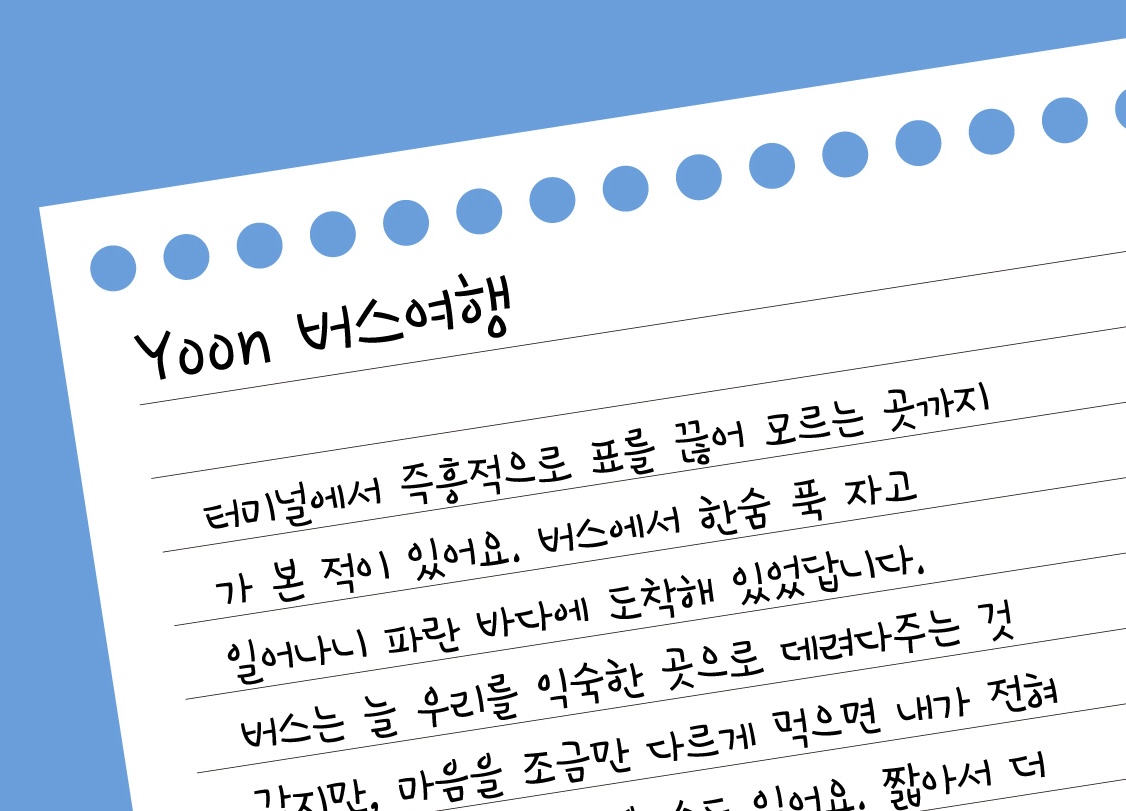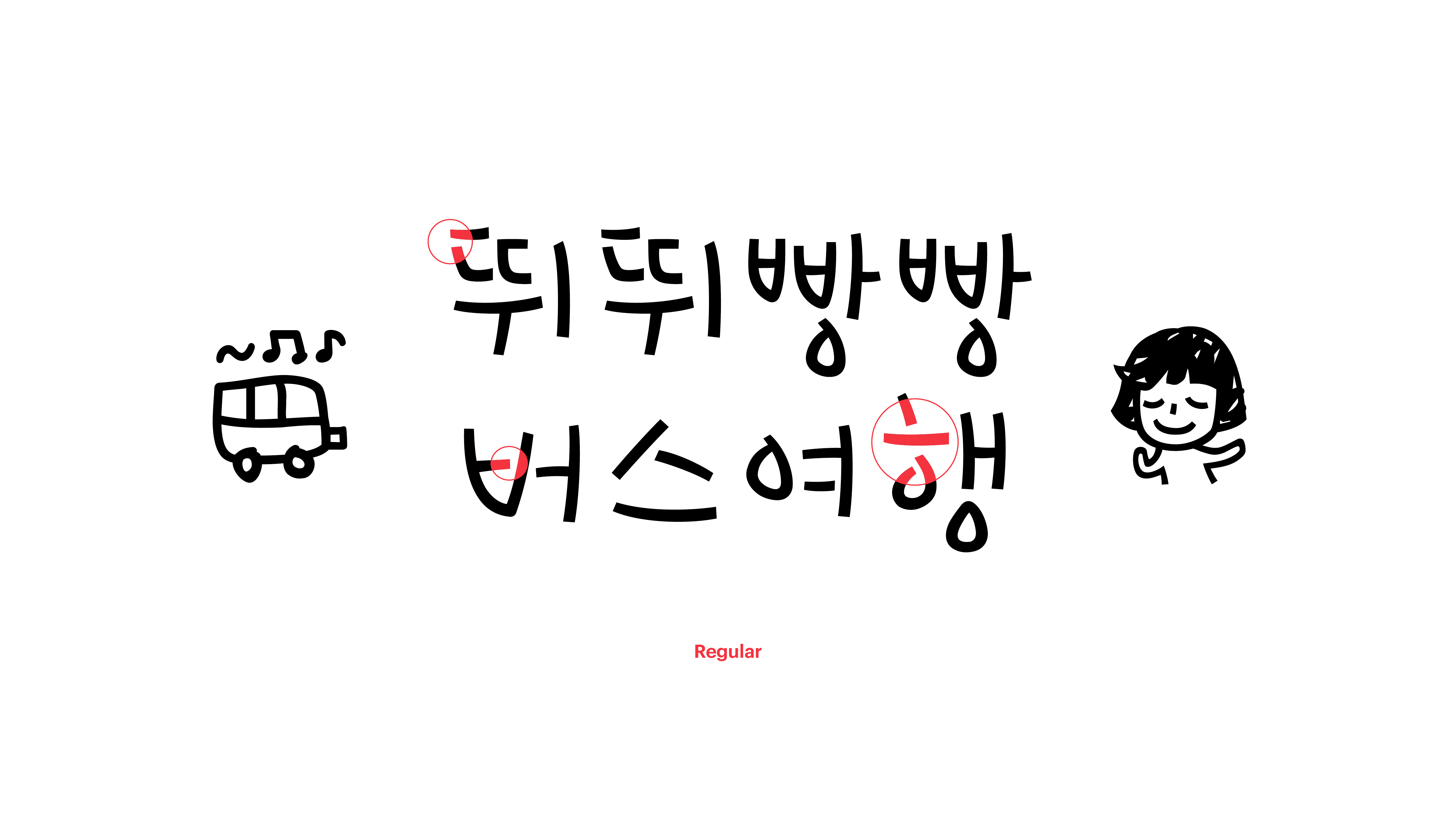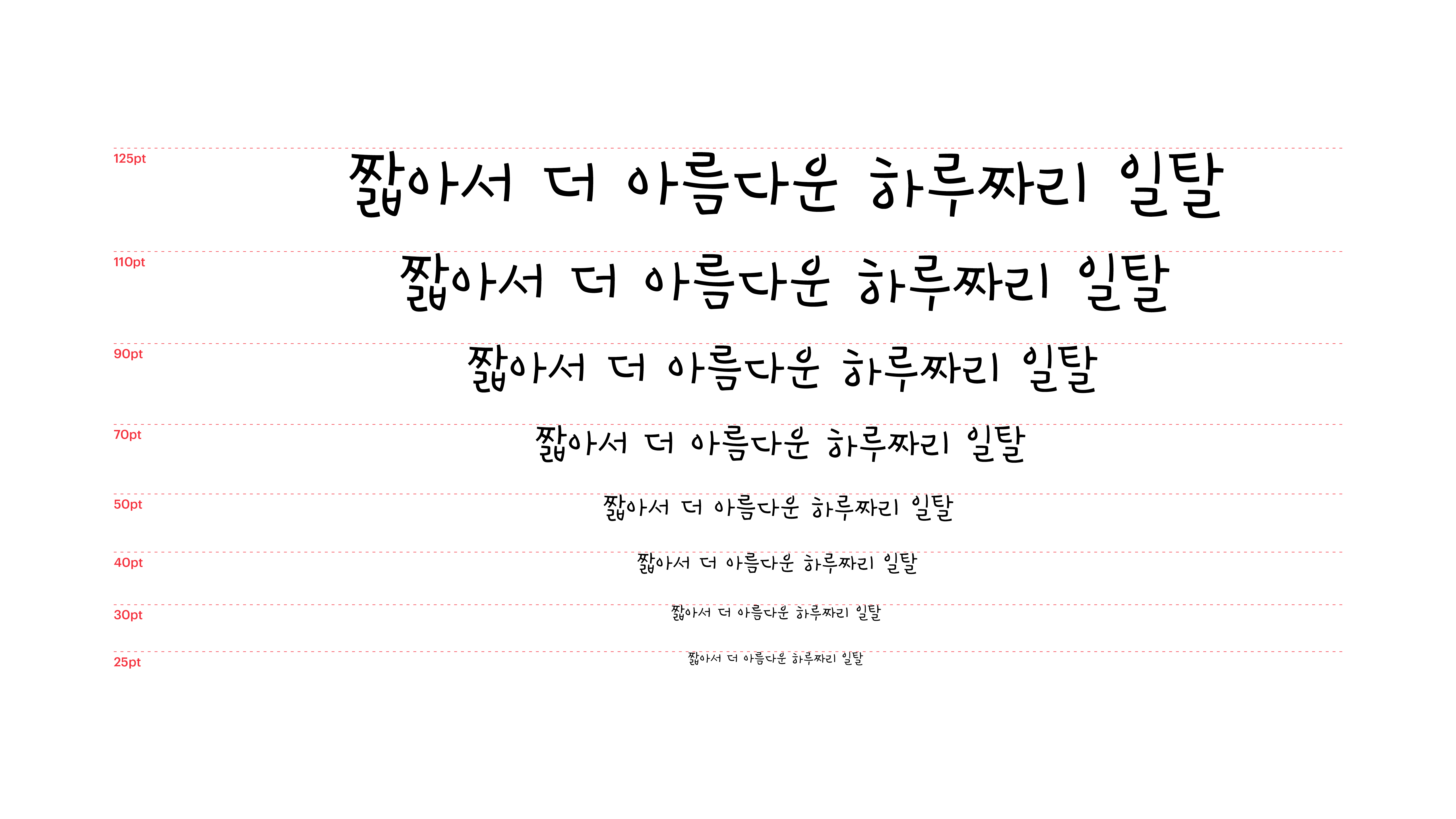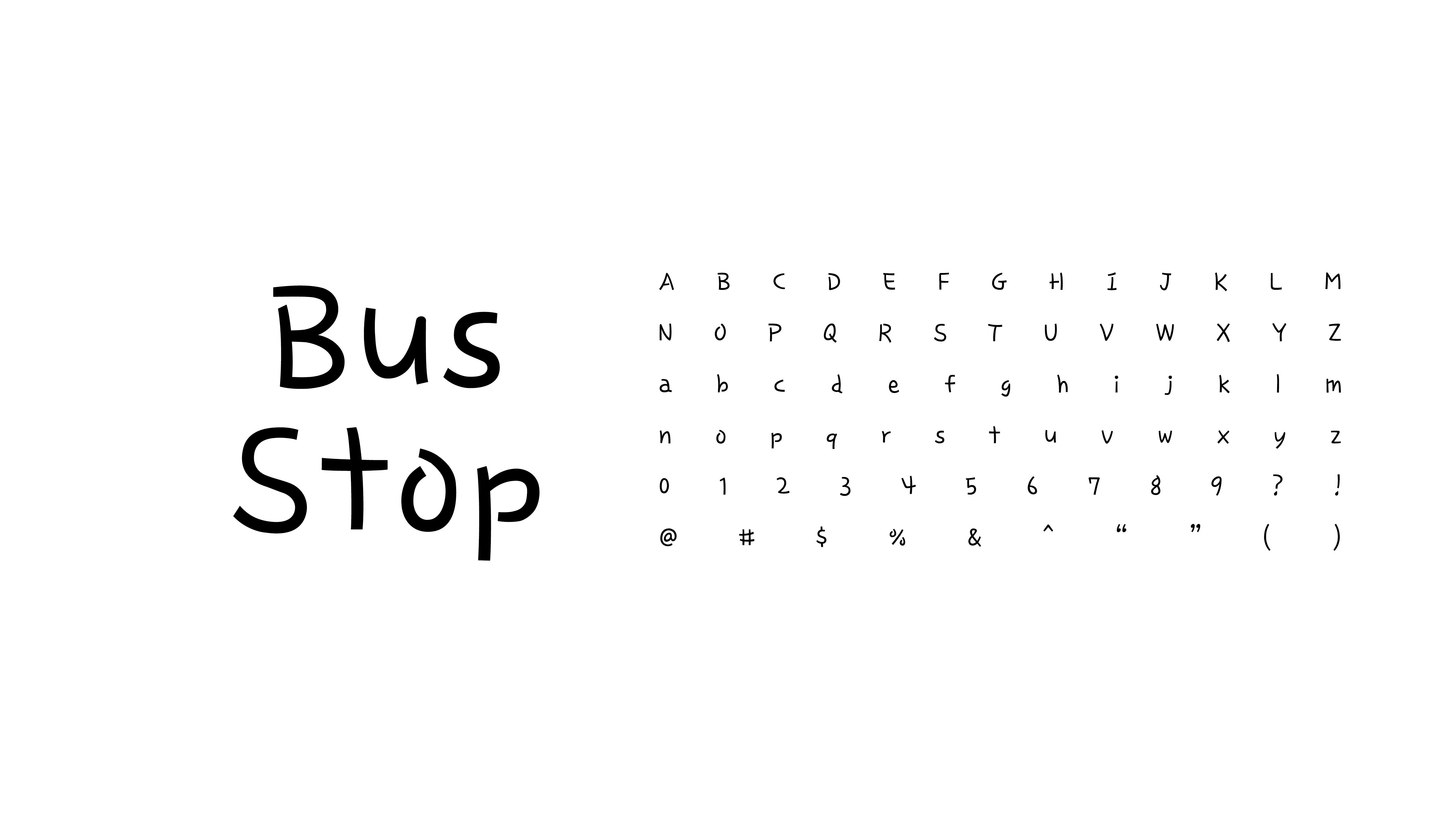
Yoon 버스여행
터미널에서 즉흥적으로 표를 끊어 모르는 곳까지 가 본 적이 있어요. 버스에서 한숨 푹 자고 일어나니 파란 바다에 도착해 있었답니다. 버스는 늘 우리를 익숙한 곳으로 데려다주는 것 같지만, 마음을 조금만 다르게 먹으면 내가 전혀 몰랐던 곳에 닿아 있을 수도 있어요. 짧아서 더 아름다운 하루짜리 일탈, 버스여행체는 그런 감성을 담아낸 자유로운 폰트랍니다.